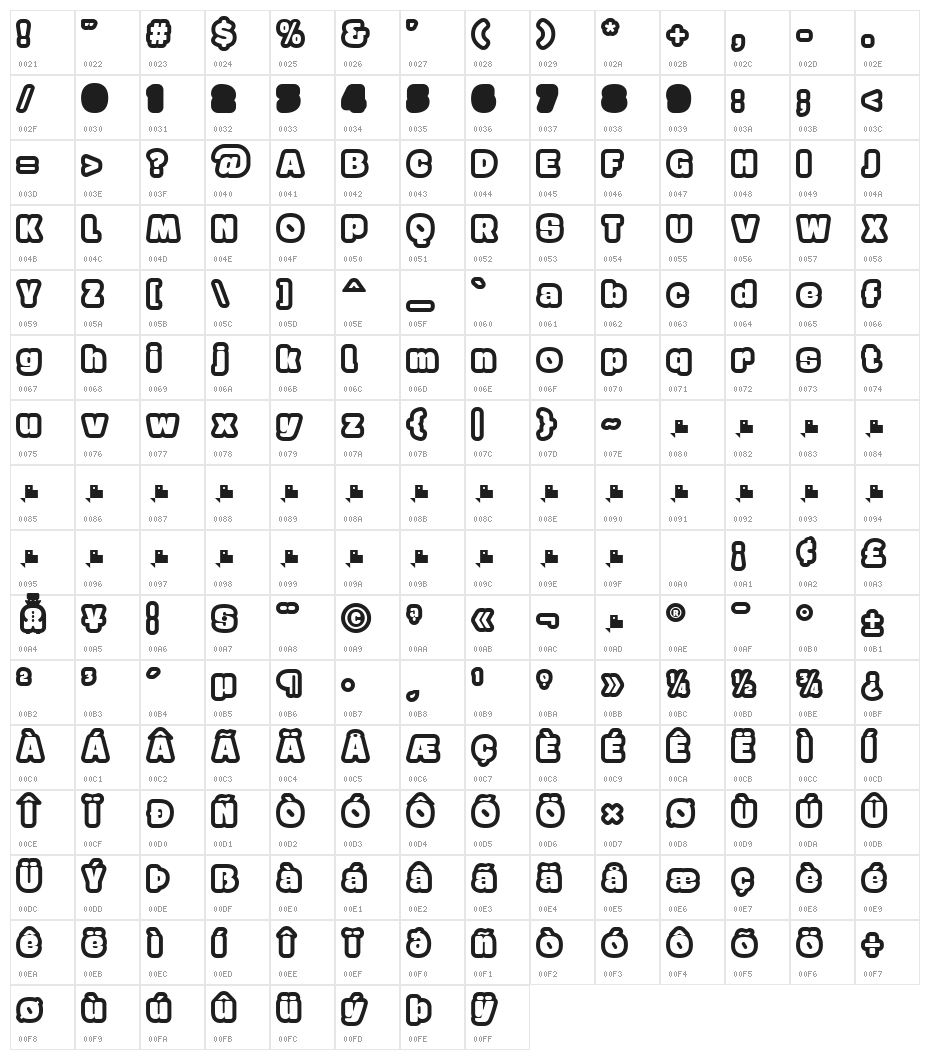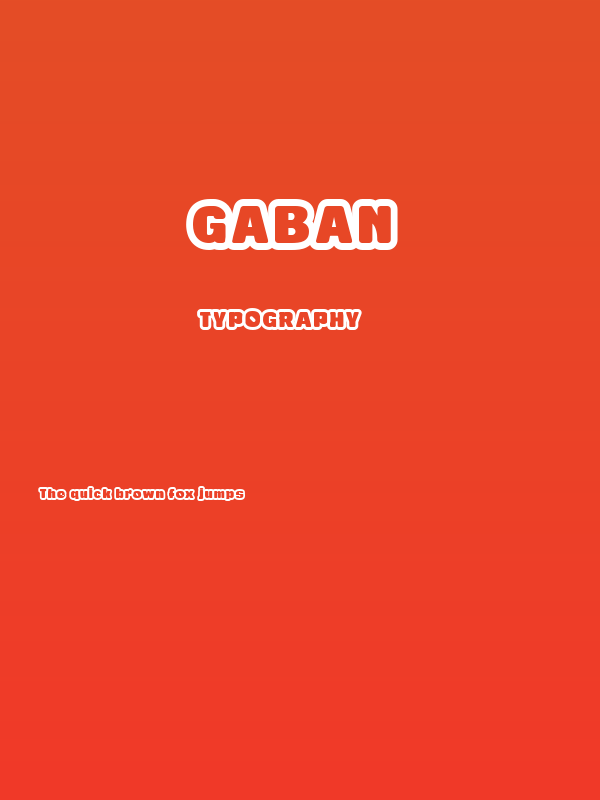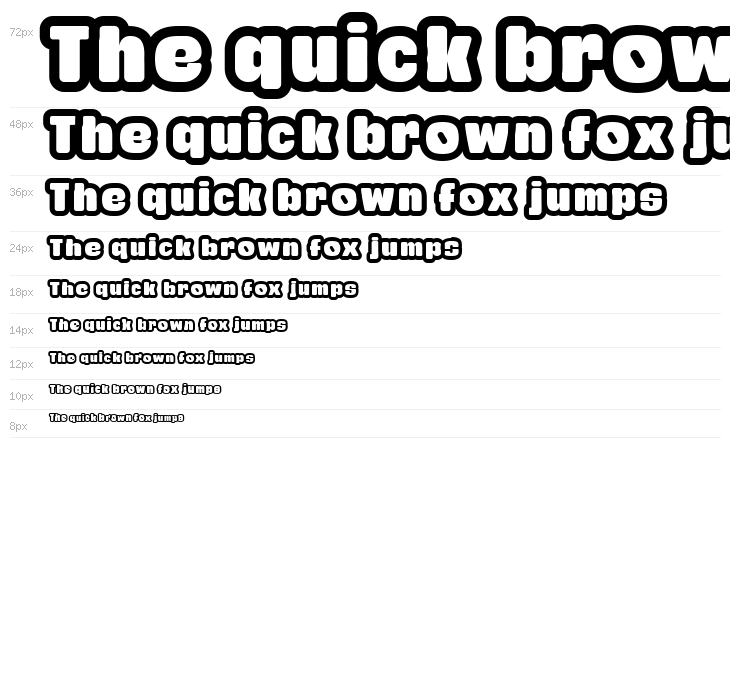
Gaban Font
| Gesamtstil | Playful, Fun |
| Vorgeschlagene Projekte | Ideal for children's books, playful branding, posters, and any design needing a bold, fun aesthetic. |